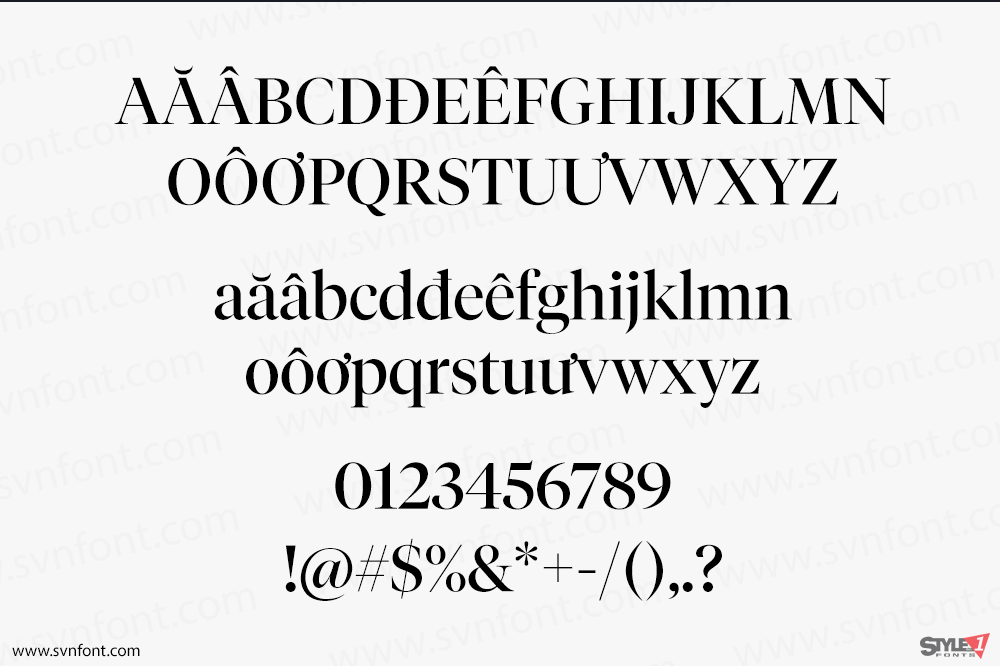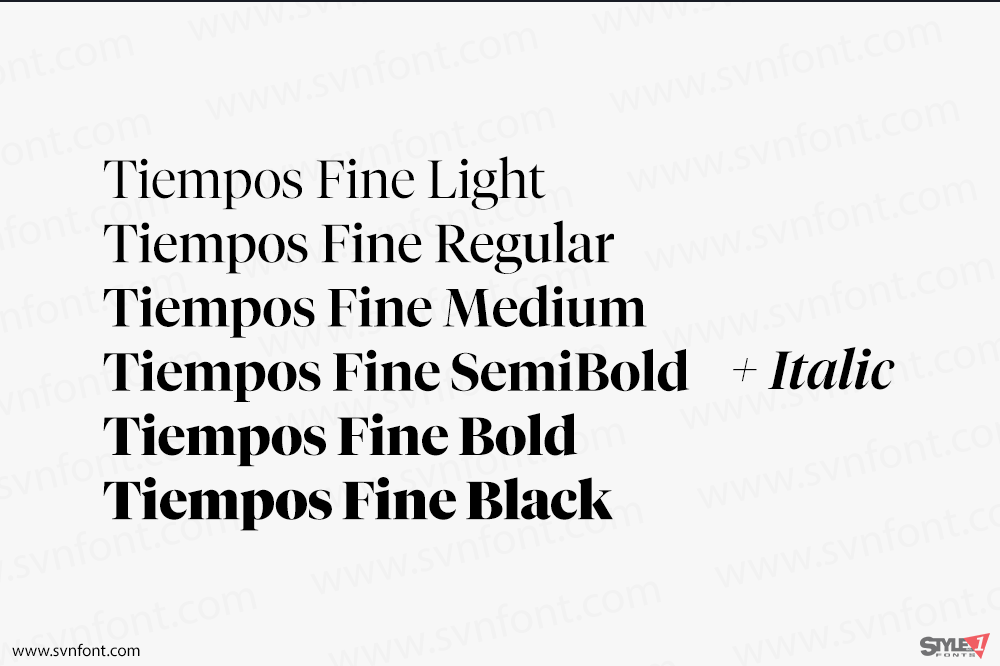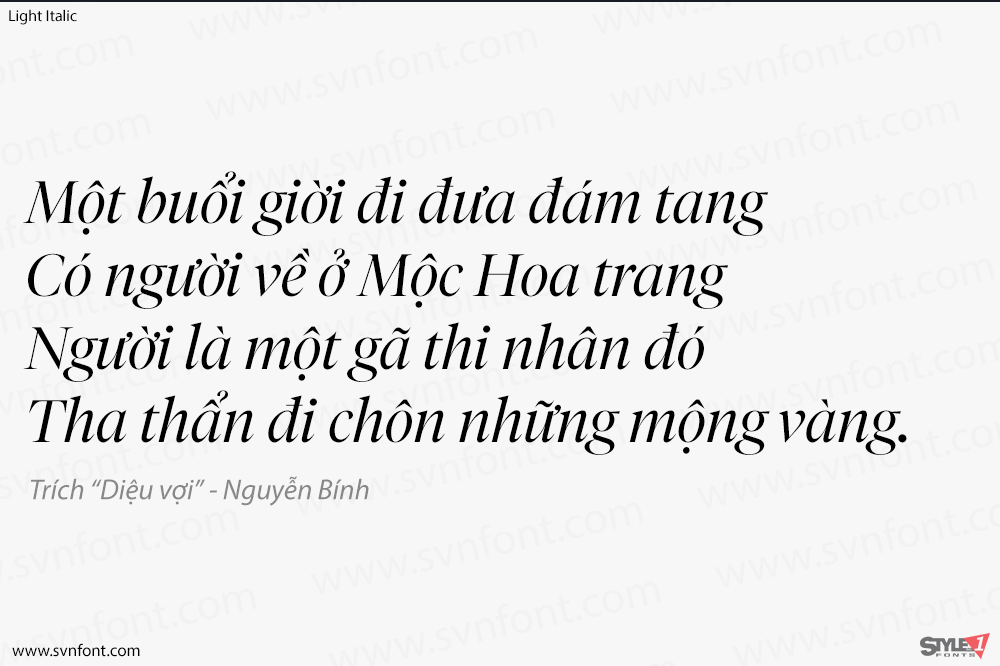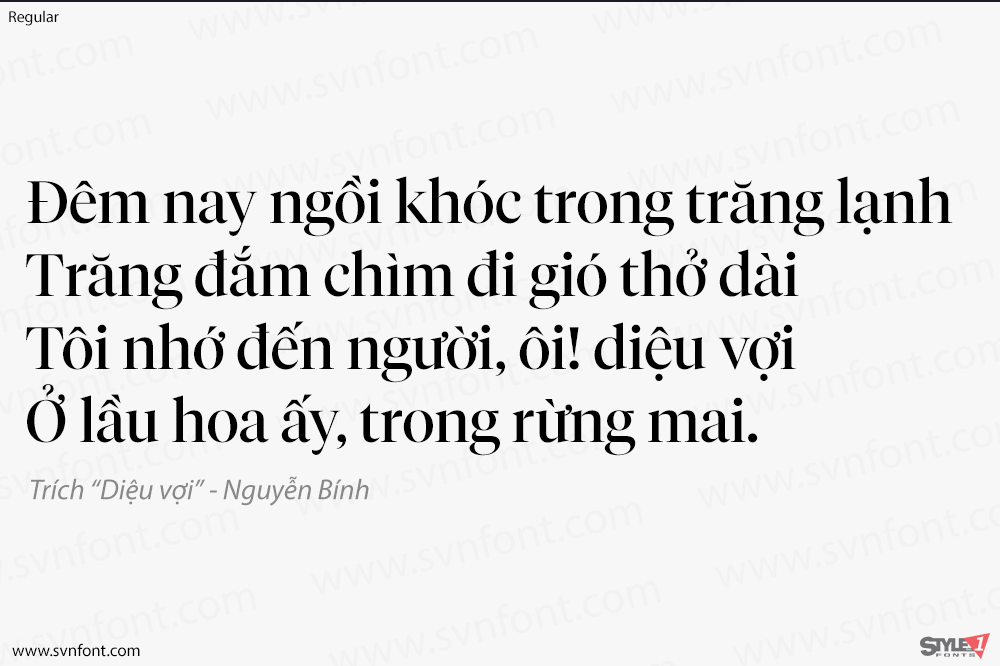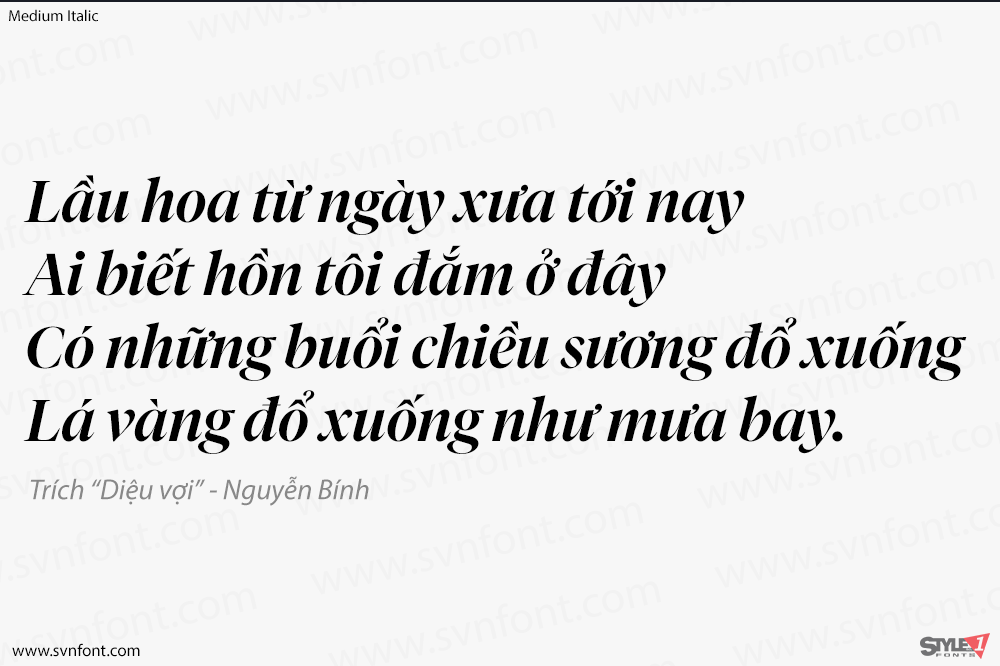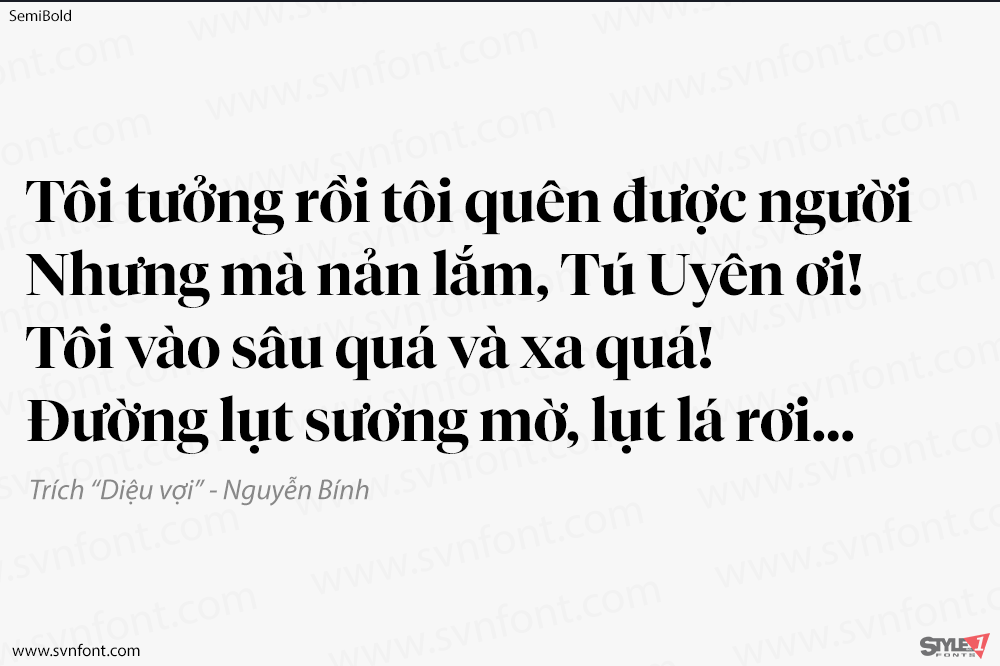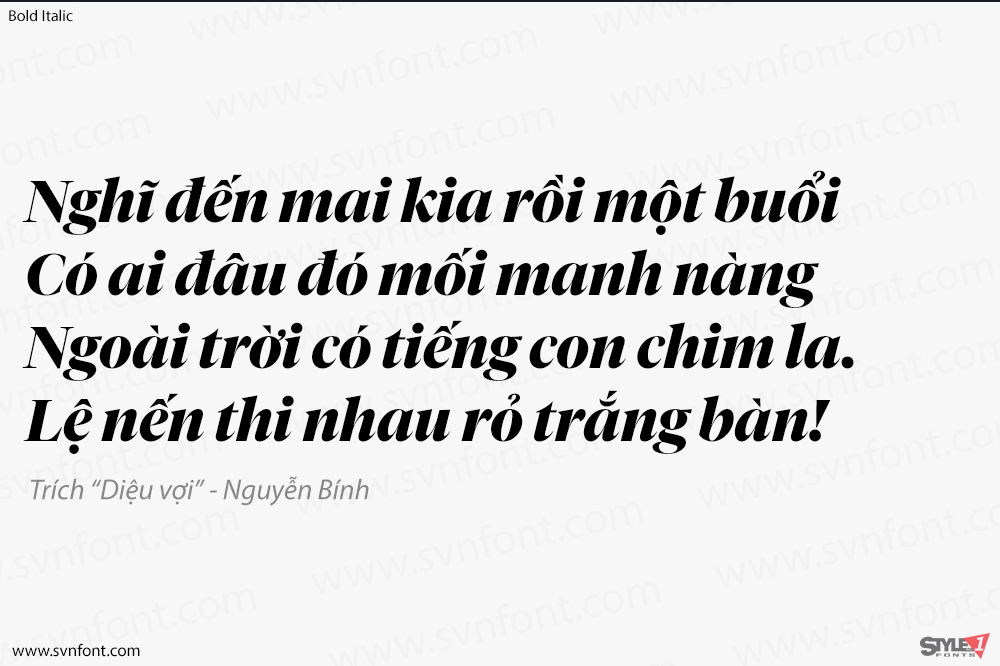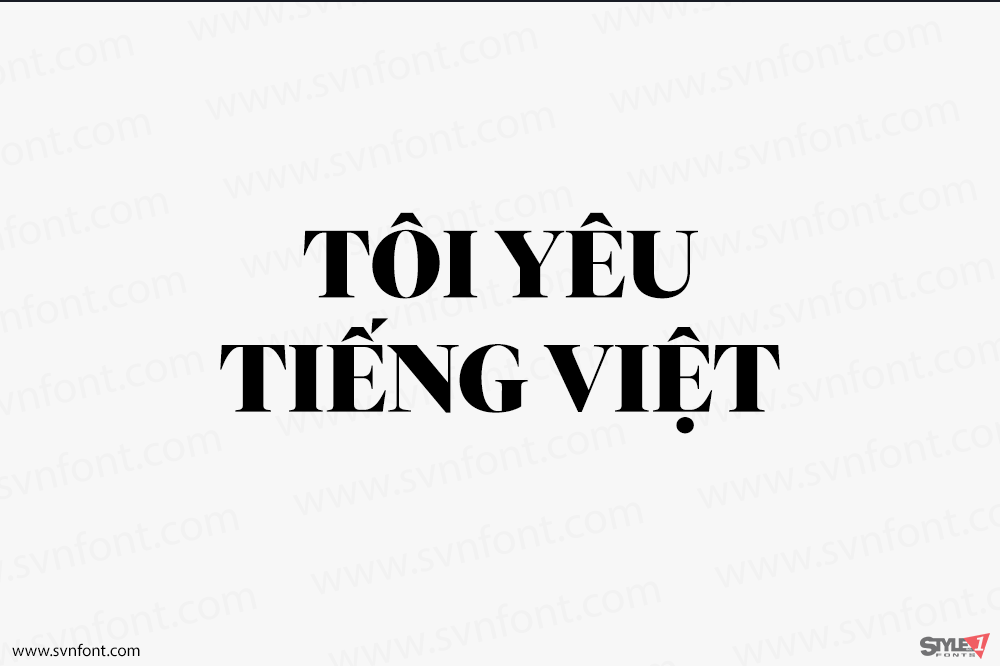
Bộ sưu tập Tiempos là một họ phông chữ serif hiện đại dành cho in ấn biên tập. Tiempos Text kế thừa tính năng của Plantin và Times, nhẹ nhàng cập nhật nó cho việc sử dụng đương đại. Nó mạnh mẽ và rõ ràng, hoàn hảo cho việc sắp chữ tiết kiệm và dễ đọc. Tiempos Headline được thiết kế cho các tiêu đề lớn hơn, tạo sự cân bằng giữa tính thực tế và sự thanh lịch. Tiempos Fine giữ nguyên tỷ lệ và sự vừa vặn của chữ cái trong Tiempos Headline, đồng thời tăng cường sự tương tác giữa các đường cong ấm áp và các chi tiết sắc nét.
Nhà thiết kế: Kris Sowersby, Noe Blanco